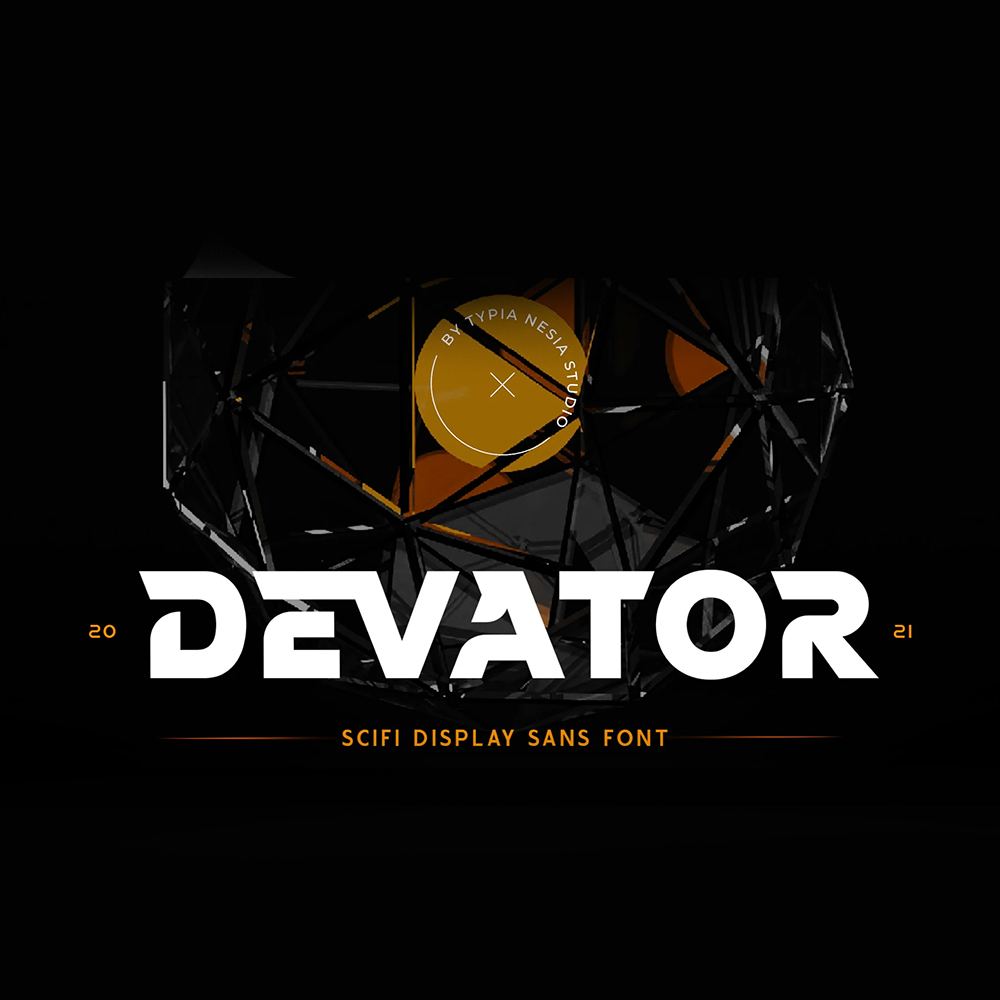
فونت پرمیوم و انگلیسی Devator Font یک فونت نمایشی و برای پروژههایی مانند لوگوها، طراحی سرمقاله، صنعت بازی، مسابقات ورزشی، برندهای سوپراسپرت، پوسترهای موسیقی، طراحی وبسایت، طراحی تبلیغات مدرن، نقل قولهای پوستر، عناوین کتاب/جلد، رویدادهای ویژه و غیره مناسب است.
مزایای استفاده از فونت لاتین Devator Font چیست؟